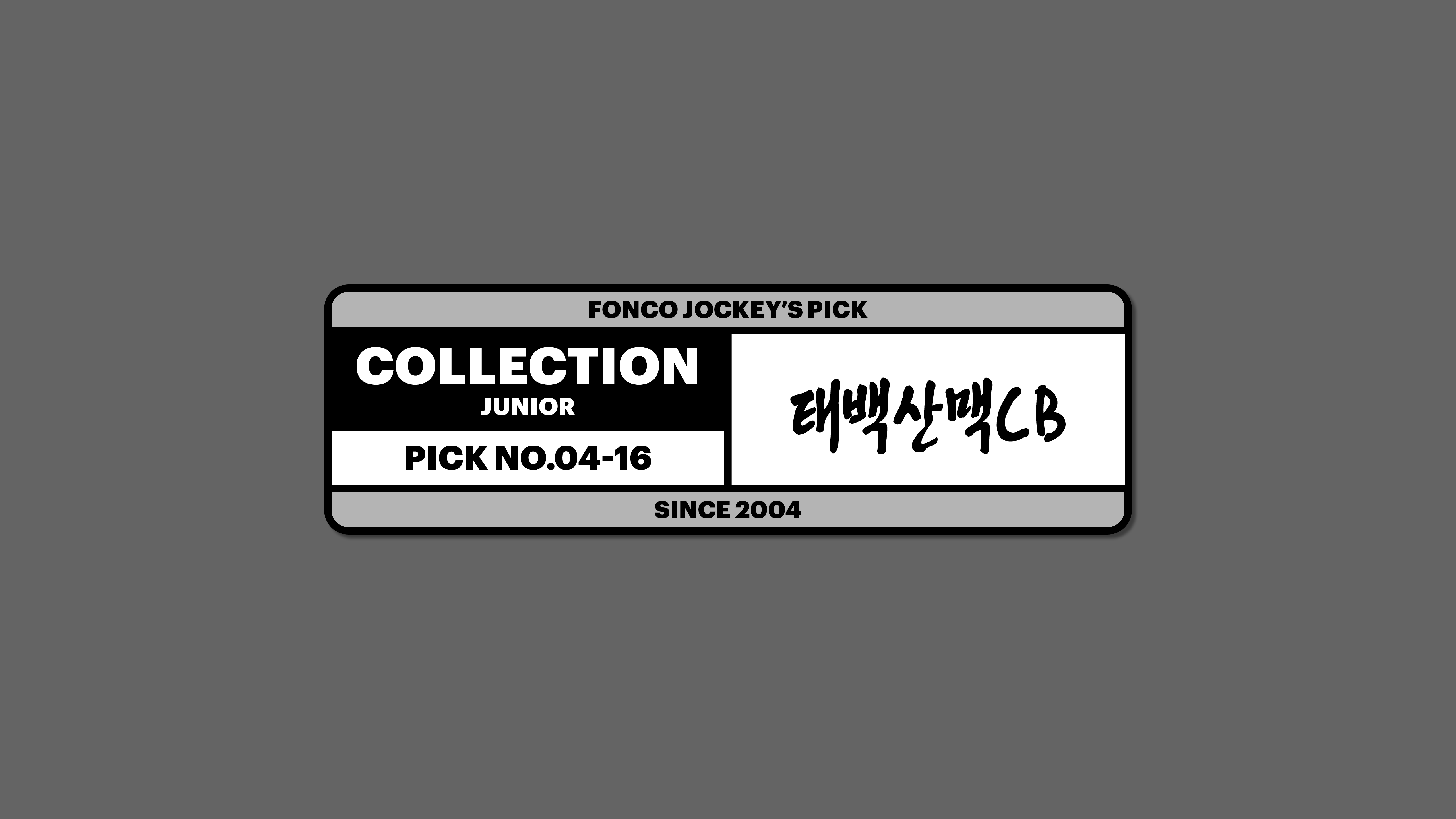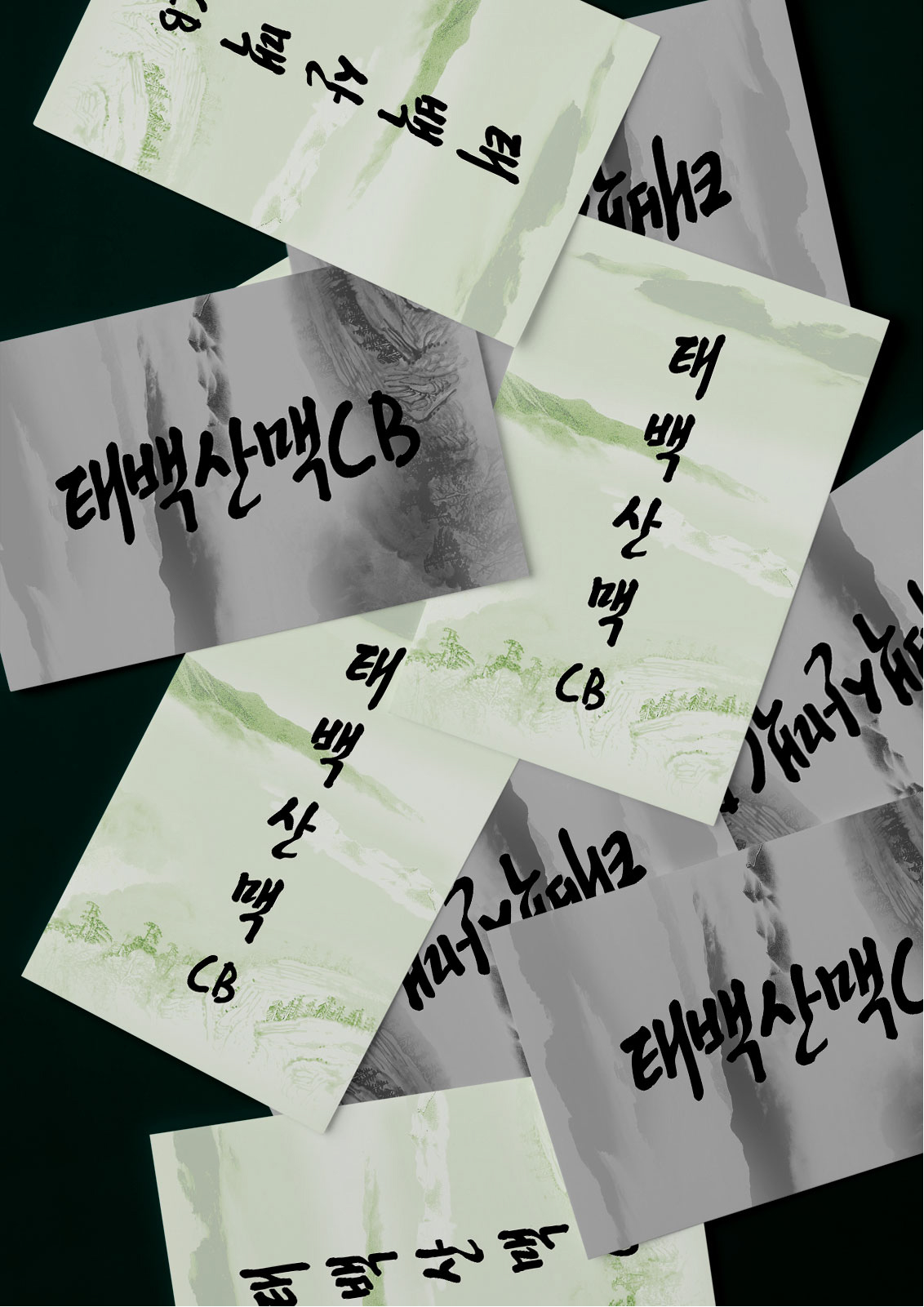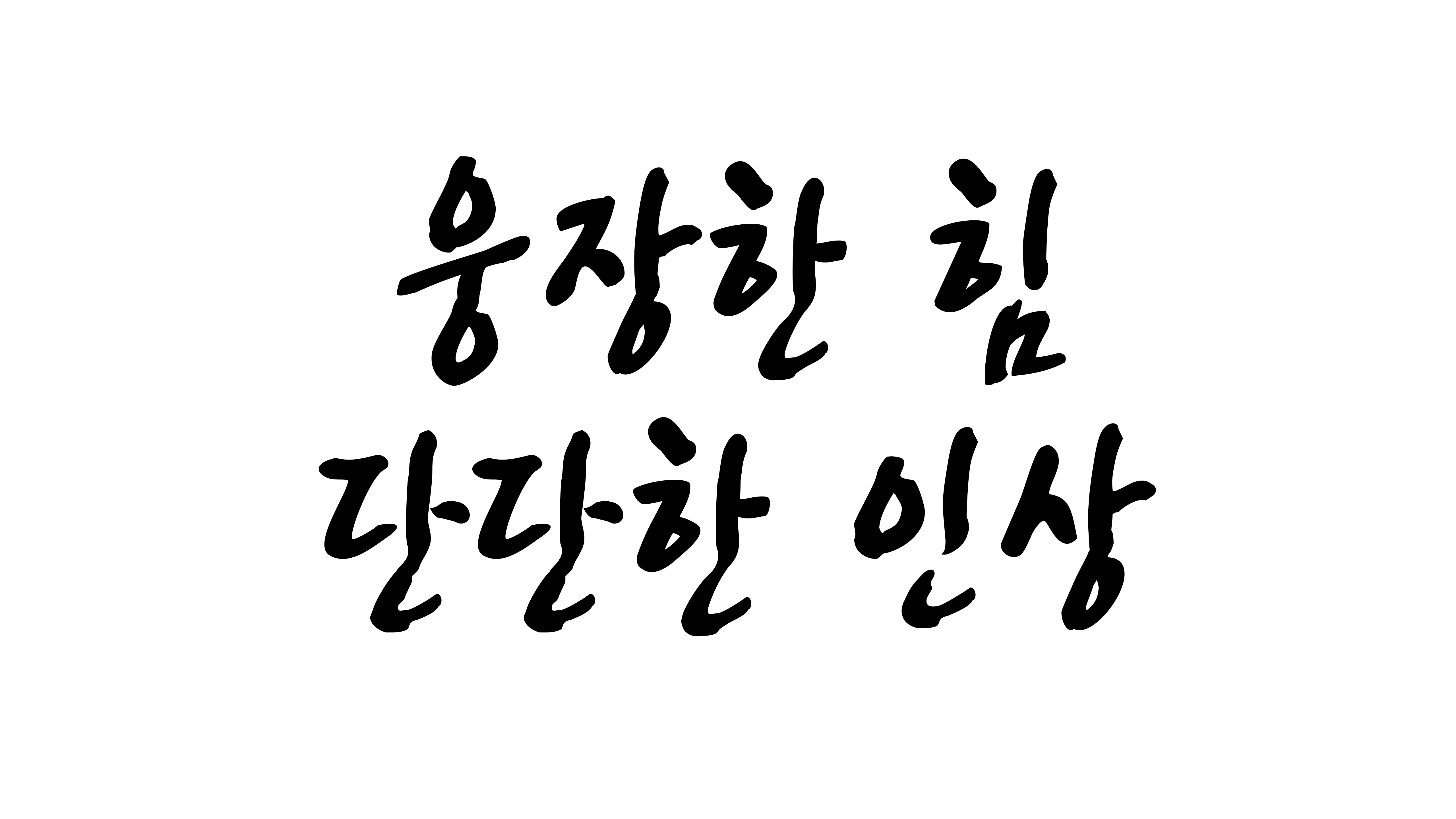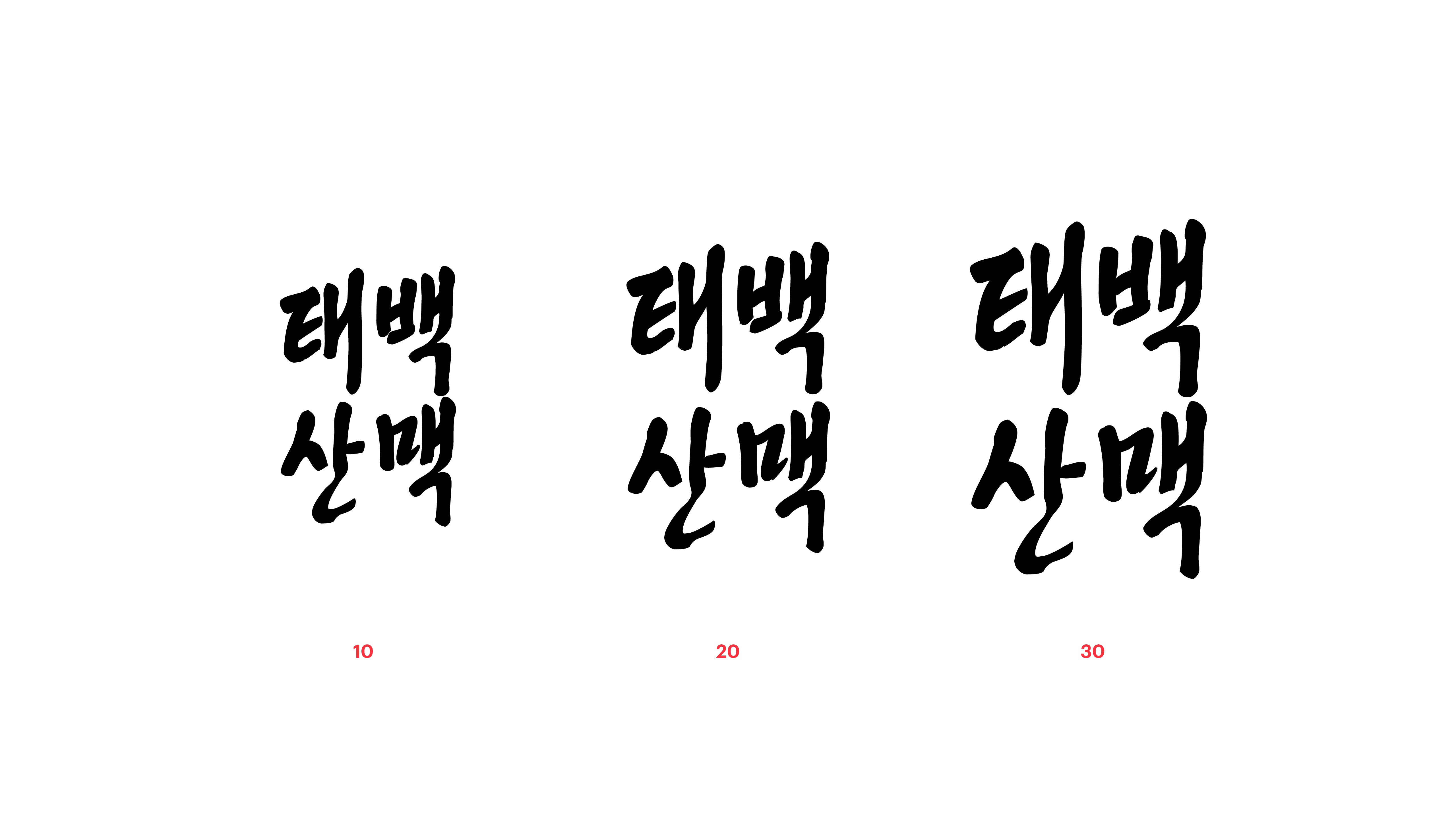
[손글씨]
태백산맥CB
Yoon 태백산맥CB
우리나라에서 가장 큰 산맥인 태백산맥의 강한 힘과 에너지를 품은 폰트입니다. 그 에너지를 강조하기 위해 기본 굵기를 Bold로 설정, 단단한 인상을 선사하고자 했지요. 더욱 강력하면서도 웅장한 힘을 느끼고 싶을 땐 Condensed Bold를 활용해 보세요. 필력의 조절만으로 전혀 다른 느낌을 전한답니다.